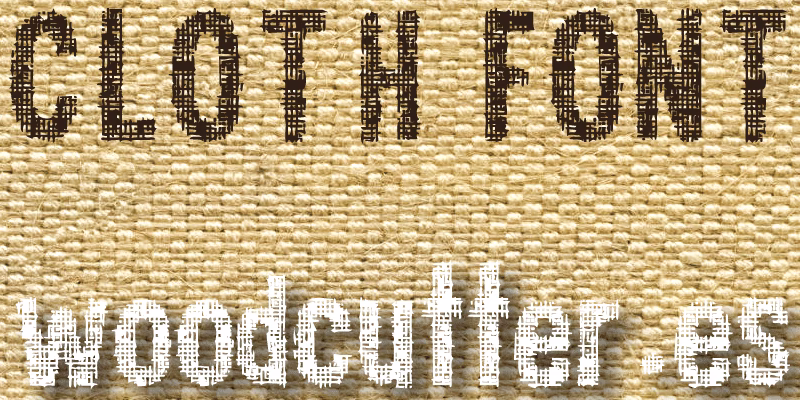
En el vasto universo del diseño gráfico y la comunicación visual, la elección de la tipografía es una de las decisiones más cruciales. Una fuente no solo transmite palabras, sino también emociones, personalidad y un tono específico. En la búsqueda de claridad, modernidad y elegancia, los diseñadores a menudo se inclinan por tipografías que encapsulan estos valores. Aquí es donde entra en escena Clother, una fuente sans-serif geométrica que se ha convertido en una herramienta poderosa para proyectos contemporáneos.
¿Qué es Exactamente la Fuente Clother?
Clother es una tipografía que pertenece a la familia de las sans-serif, también conocidas como de "palo seco". Esto significa que sus caracteres carecen de las pequeñas terminaciones o remates (serifas) que se ven en fuentes más tradicionales como Times New Roman. Pero Clother va un paso más allá: se clasifica como una sans-serif geométrica. Este apellido no es casual; implica que su construcción se basa en formas geométricas puras como círculos, cuadrados y triángulos. El resultado es una apariencia increíblemente limpia, estructurada y equilibrada. La esencia de Clother radica en su simplicidad y precisión. Cada letra está diseñada con líneas nítidas y un grosor de trazo notablemente consistente. No hay adornos innecesarios ni florituras; cada elemento tiene un propósito. Esta filosofía de diseño la convierte en un vehículo perfecto para mensajes que requieren ser directos, honestos y tecnológicamente avanzados. Su espaciado uniforme entre caracteres asegura una lectura fluida y agradable, evitando la fatiga visual tanto en soportes digitales como impresos.
Características Clave que Definen a Clother
Para comprender por qué Clother es tan apreciada en el mundo del diseño, es fundamental desglosar sus atributos principales. Estas características no solo la definen, sino que también explican su gran versatilidad.
- Modernidad y Minimalismo: En una era donde "menos es más", Clother encarna a la perfección la estética minimalista. Su diseño despojado de ornamentos la hace ideal para interfaces de usuario, sitios web y marcas que quieren proyectar una imagen actual, fresca y profesional.
- Legibilidad Superior: La combinación de su trazo uniforme y sus formas geométricas claras la dota de una legibilidad excepcional. Funciona de maravilla en tamaños pequeños en pantallas de alta resolución y mantiene su claridad en grandes titulares de carteles o vallas publicitarias. Es una fuente que no sacrifica la función por la forma.
- Estructura Geométrica Pura: Letras como la 'O' son círculos casi perfectos, mientras que la 'M' o la 'N' presentan ángulos precisos y definidos. Esta base matemática le confiere una sensación de estabilidad, orden y confianza, cualidades muy valoradas en el diseño corporativo.
- Versatilidad de Aplicación: A diferencia de fuentes muy estilizadas que solo funcionan en contextos específicos, Clother es un verdadero camaleón. Es lo suficientemente elegante para un logo de una marca de lujo y lo suficientemente clara para el cuerpo de texto de un informe anual.
Aplicaciones Ideales: ¿Dónde Brilla la Fuente Clother?
La flexibilidad de Clother le permite adaptarse a una multitud de proyectos. A continuación, exploramos algunos de los escenarios donde su uso puede marcar una diferencia significativa en el impacto visual del proyecto.
Branding y Diseño de Logos
Para las empresas que buscan construir una identidad de marca moderna, tecnológica o minimalista, Clother es una elección sobresaliente. Su claridad garantiza que el logo será legible en cualquier tamaño, desde un favicon en una pestaña del navegador hasta un letrero en un edificio. Transmite profesionalismo y eficiencia sin resultar fría o impersonal.
Diseño Web y de Interfaces (UI)
En el diseño de interfaces digitales, la claridad es el rey. Clother es perfecta para titulares, botones, menús de navegación y textos descriptivos en aplicaciones y sitios web. Su rendimiento en pantalla es excelente, asegurando que la experiencia del usuario sea fluida y sin fricciones. Su naturaleza geométrica se complementa a la perfección con los diseños basados en cuadrículas y layouts estructurados.
Material Impreso y Editorial
Desde folletos y catálogos hasta revistas y cartelería, Clother aporta un aire de sofisticación y orden. Es una opción fantástica para titulares que necesitan captar la atención de inmediato, pero también puede funcionar en bloques de texto cortos, como descripciones de productos o pies de foto, gracias a su excelente legibilidad.
Tabla Comparativa de Estilos Tipográficos
Para poner en perspectiva las fortalezas de Clother, es útil compararla con otros estilos de fuentes comunes.
| Característica | Clother (Sans-Serif Geométrica) | Fuente Serif Clásica | Fuente Script (Decorativa) |
|---|---|---|---|
| Sensación / Tono | Moderno, limpio, objetivo, tecnológico. | Tradicional, elegante, formal, literario. | Personal, artístico, informal, emotivo. |
| Legibilidad en Pantalla | Excelente. Diseñada para la claridad digital. | Buena, aunque las serifas pueden dificultar la lectura en tamaños muy pequeños. | Baja. No recomendada para textos de interfaz. |
| Uso en Párrafos Largos | Bueno, especialmente en web. | Excelente. Considerada el estándar para libros y textos extensos. | Inadecuado. Cansa la vista rápidamente. |
| Ideal Para... | Branding, UI/UX, titulares, diseño corporativo. | Libros, periódicos, documentos académicos, marcas de lujo. | Invitaciones, logos de autor, citas destacadas. |